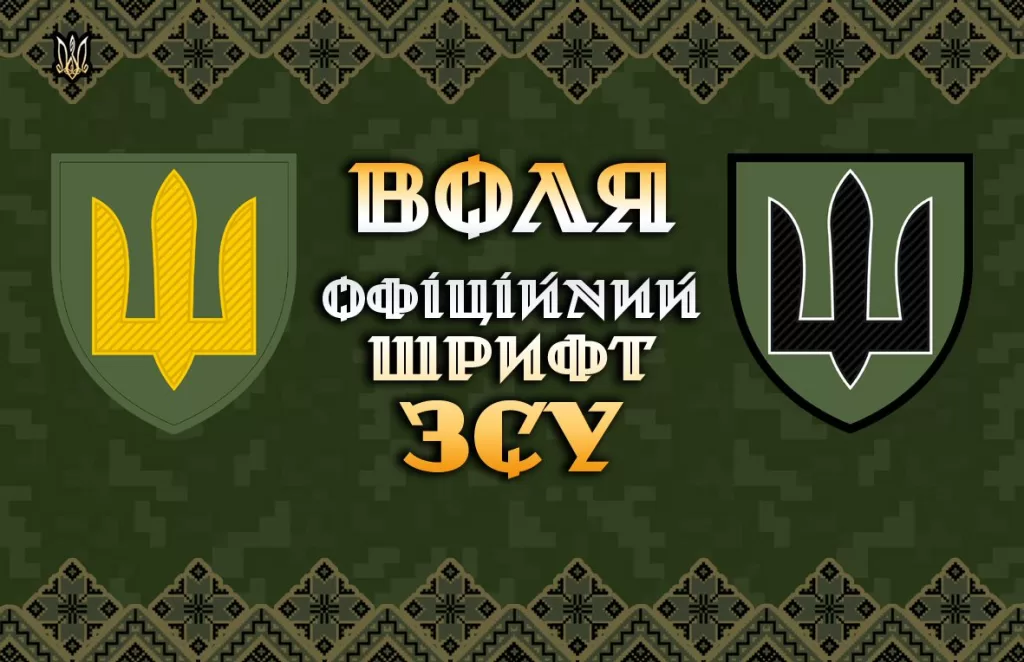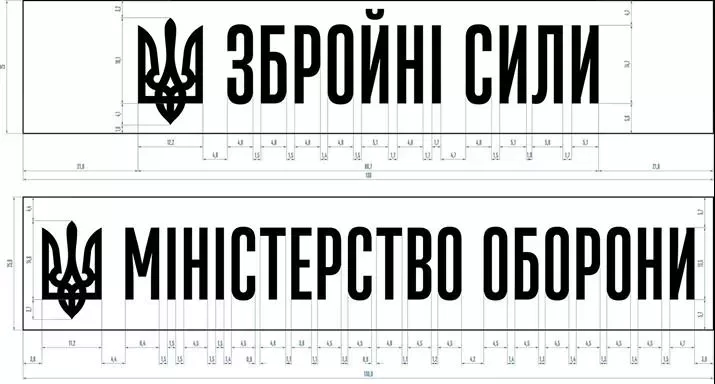
Нова комунікаційна стратегія ЗСУ була затверджена Головнокомандувачем Збройних сил України Валерієм Залужним у лютому 2023 року. Наразі у публічному просторі викладено керівництво з використання графічного стилю у візуальній комунікації. Авторами нового дизайну стали: солдат 103 ОБр ТрО Тарас Іщик, шрифтові дизайнери Дмитро Растворцев, Марчела Можина та дизайнер Орест Підлісецький. На сайті студії Gravirovka.UA ви можете завантажити офіційний шрифт ЗСУ, щоб використати його для лазерного гравіювання.
Шрифт “Воля” —церемонійний шрифт ЗСУ
Церемонійний шрифт ЗСУ — “Volja” використовують для лазерного гравіювання, оформлення почесних грамот, подяк, посвідчень до нагород, нагородних листів тощо. Також його можна використовувати для нагород та бойових (почесних) прапорів військових частин ЗСУ. Шрифт Volja розробила Марчела Можина на основі типографії відомого українського графіка часів національно-визвольних змагань Ніла Хасевича.
Приклади використання в сувенірній продукції для ЗСУ
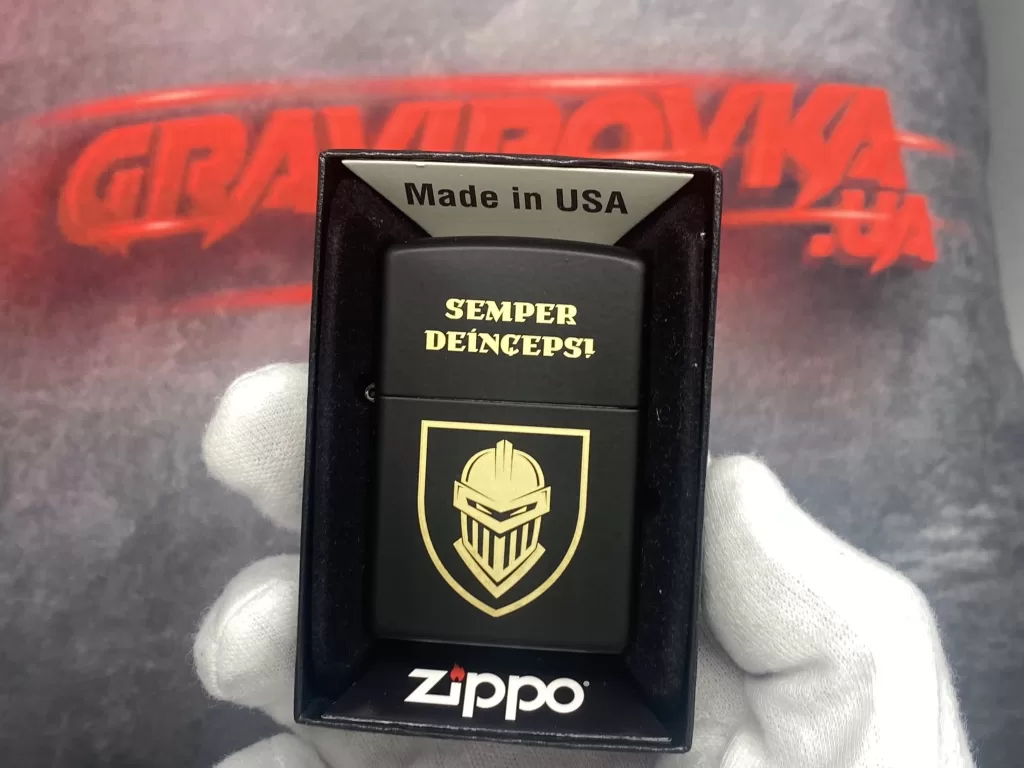
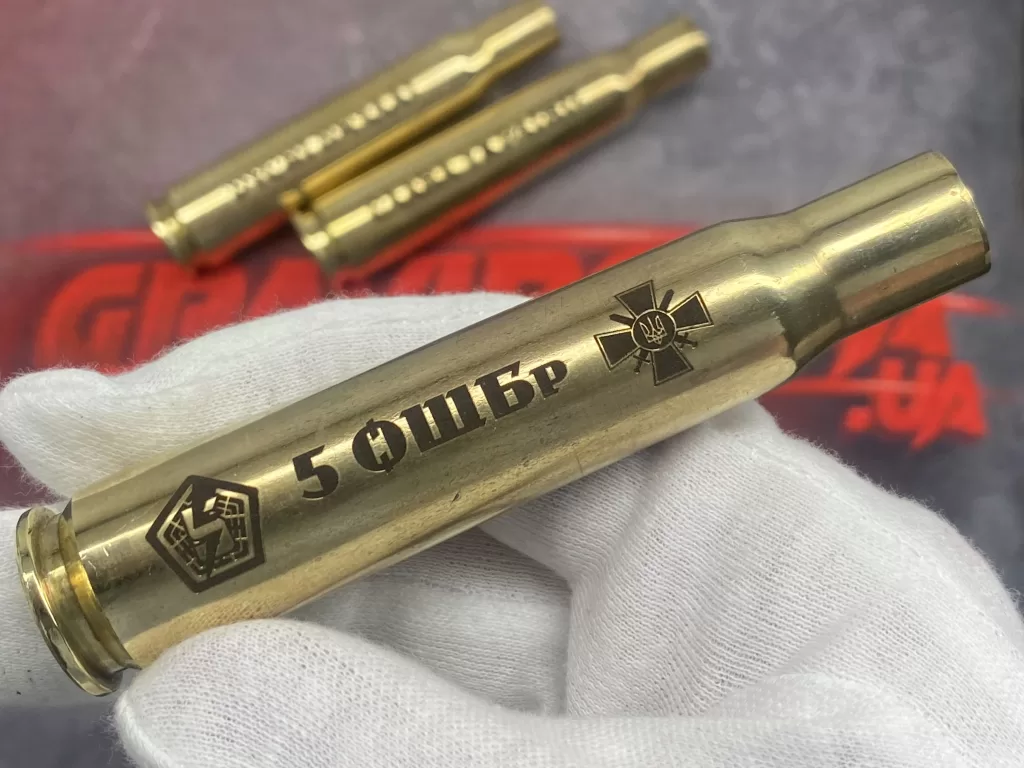
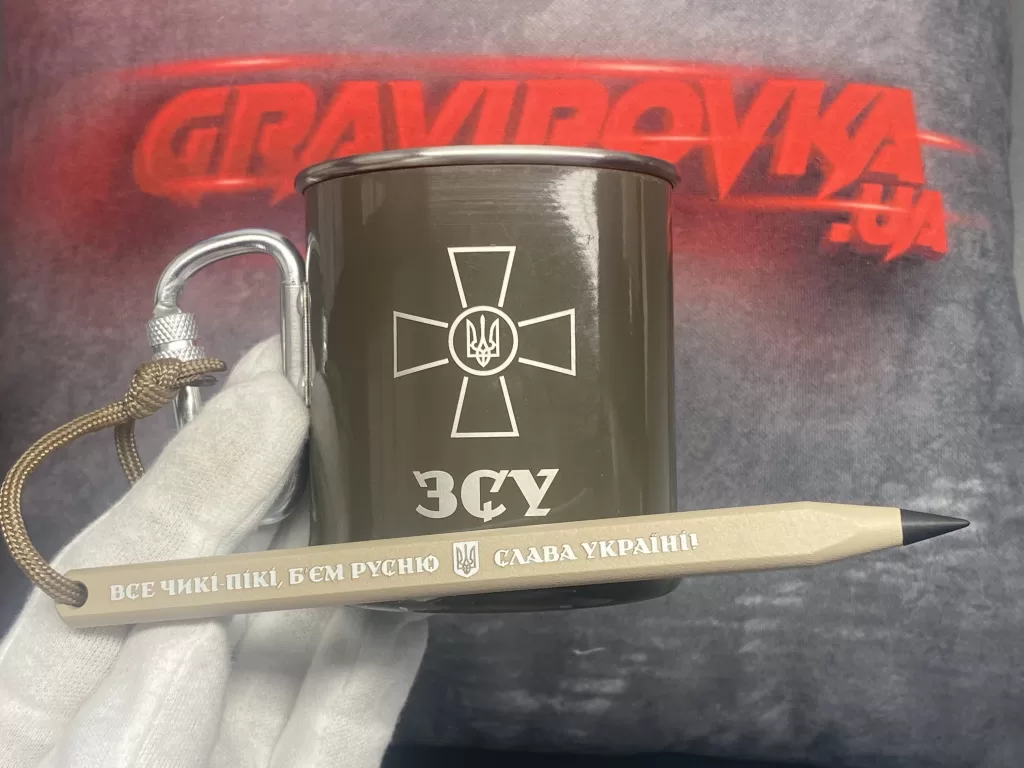
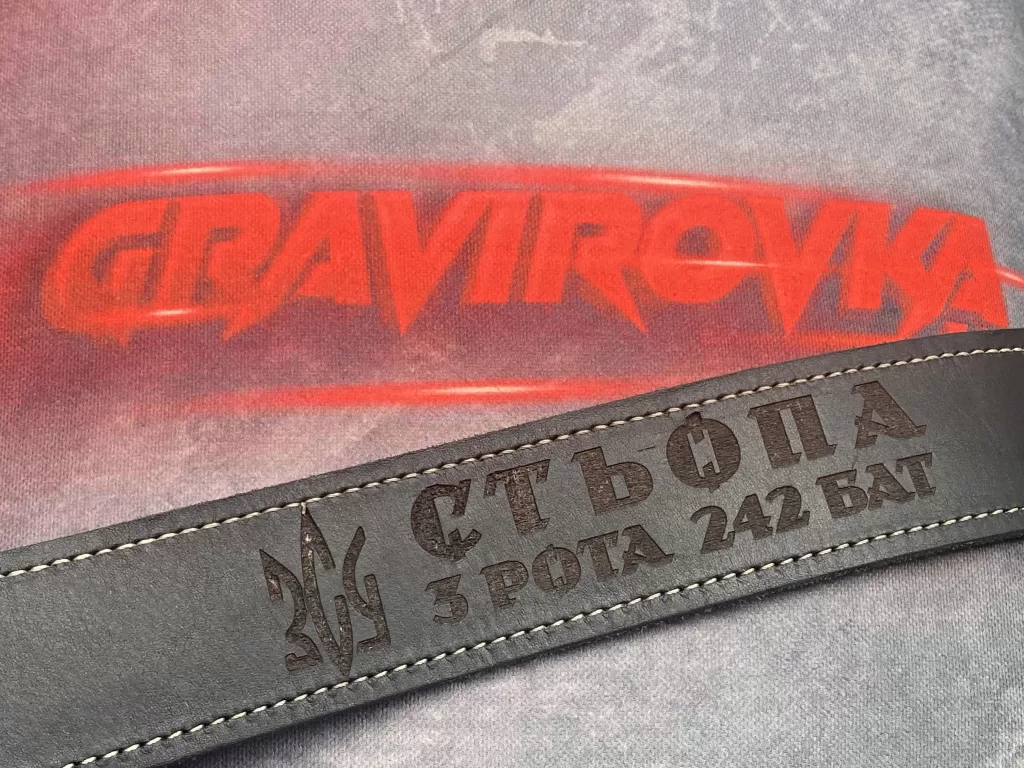
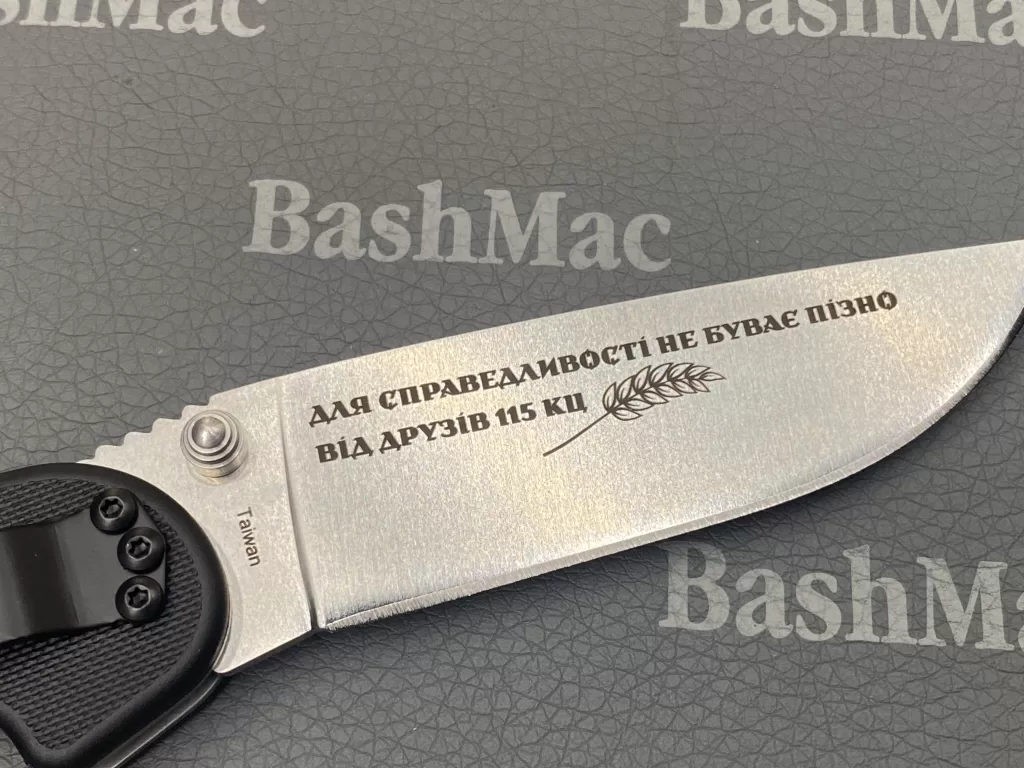
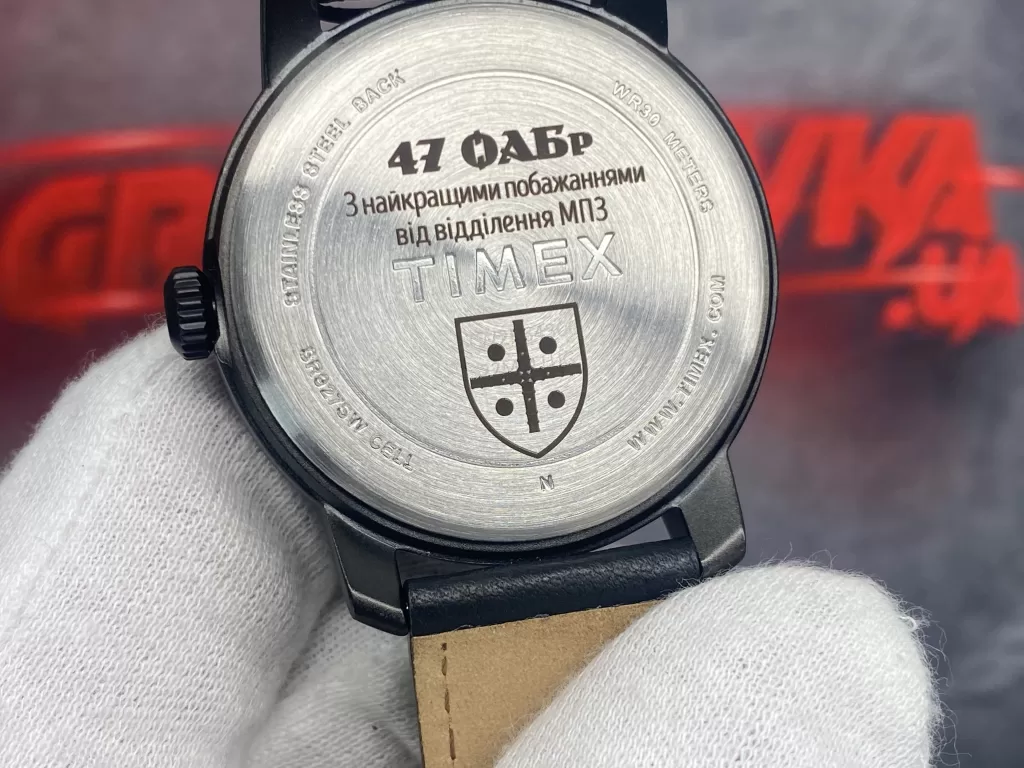
Шрифт UAF Sans — офіційний шрифт Збройних Сил України
Шрифт розробив Дмитро Растворцев. Дизайн уособлює найкращі українські шрифтові традиції, військовий стиль та задовольняє усі комунікаційні потреби Збройних Сил України. Наявне також накреслення для неймтейпів та для техніки. Відмінно підходить для гравіювання лазером.
«Літери шрифту UAF Sans мають по 10-12 референсів з різних літер українських шрифтотворців початку XX століття. Окремі елементи надають шрифту мілітарний стиль. Оскільки шрифт є більше як у 20 накресленнях, він задовольняє всі рекламні й комунікаційні потреби Збройних Сил. Однак він не призначений для текстів документів чи верстки книг. Накреслення для військової техніки дозволяють наносити бортові номери та логотипи на військову техніку після відповідних змін в бойових статутах».
Шрифт UA Army Labels Regular
У липні 2015 року Верховна Рада передала повноваження щодо розроблення та затвердження зразків військової форми одягу та загальних вимог до знаків розрізнення військовослужбовців Міністерству оборони України.
Новий шрифт, який можливо використовувати для лазерної гравіровки, отримав назву UA Army Labels Regular.
Керівництво із використання графічного стилю у візуальній комунікації ЗСУ
Одна з найголовніших змін — оновлення брендбуку. З’явилась детальна методичка — як правильно оформлювати візуал — «Керівництво із використання графічного стилю у візуальній комунікації». Тепер у розпорядженні усіх військових медійників і SMM-спеціалістів регламентовані кольори за кодами, шрифти, макети, логотипи, макетування тощо.